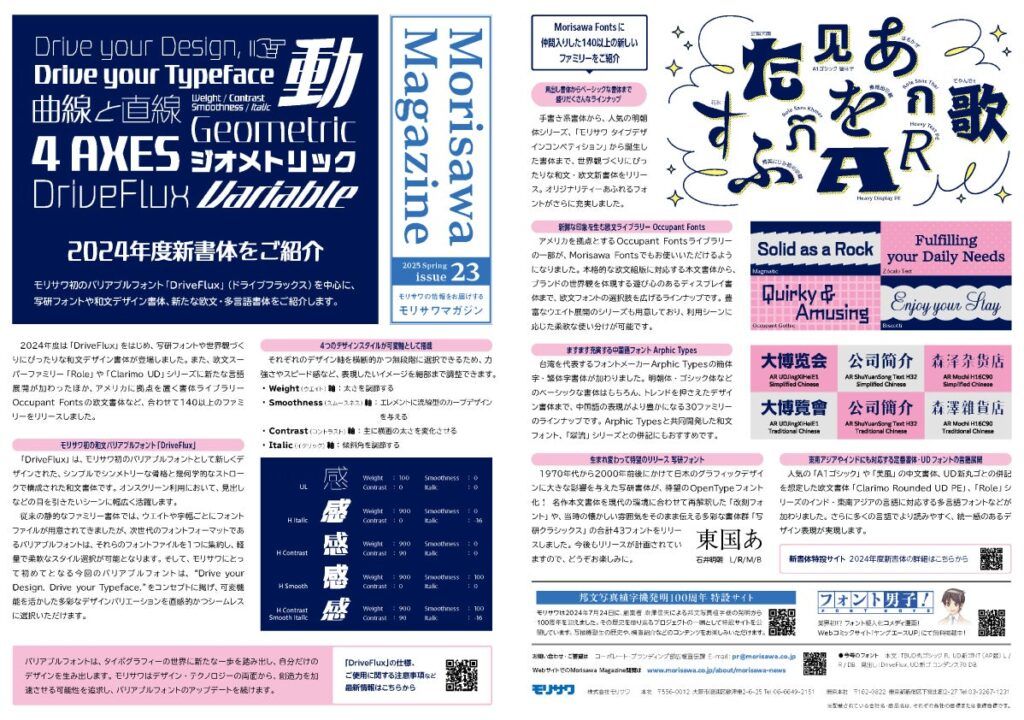
モリサワ 企業情報やDTPに関わる情報やフォントのトレンド・豆知識などを紹介する広報誌「MORISAWA MAGAZINE」23号を発行 2024年度新書体特集でモリサワ初のバリアブルフォント「DriveFlux」などを紹介
同号は2024年度新書体を特集した。モリサワ初のバリアブルフォント「DriveFlux(ドライブフラックス)」をはじめ、写研フォントや世界観づくりにぴったりな和文デザイン書体が登場。また、欧文スーパーファミリー「Role」や「Clarimo UD」シリーズに新たな言語展開が加わったほか、アメリカに拠点を置く書体ライブラリOccupant Fontsの欧文書体など、合わせて140以上のファミリーをリリースした。